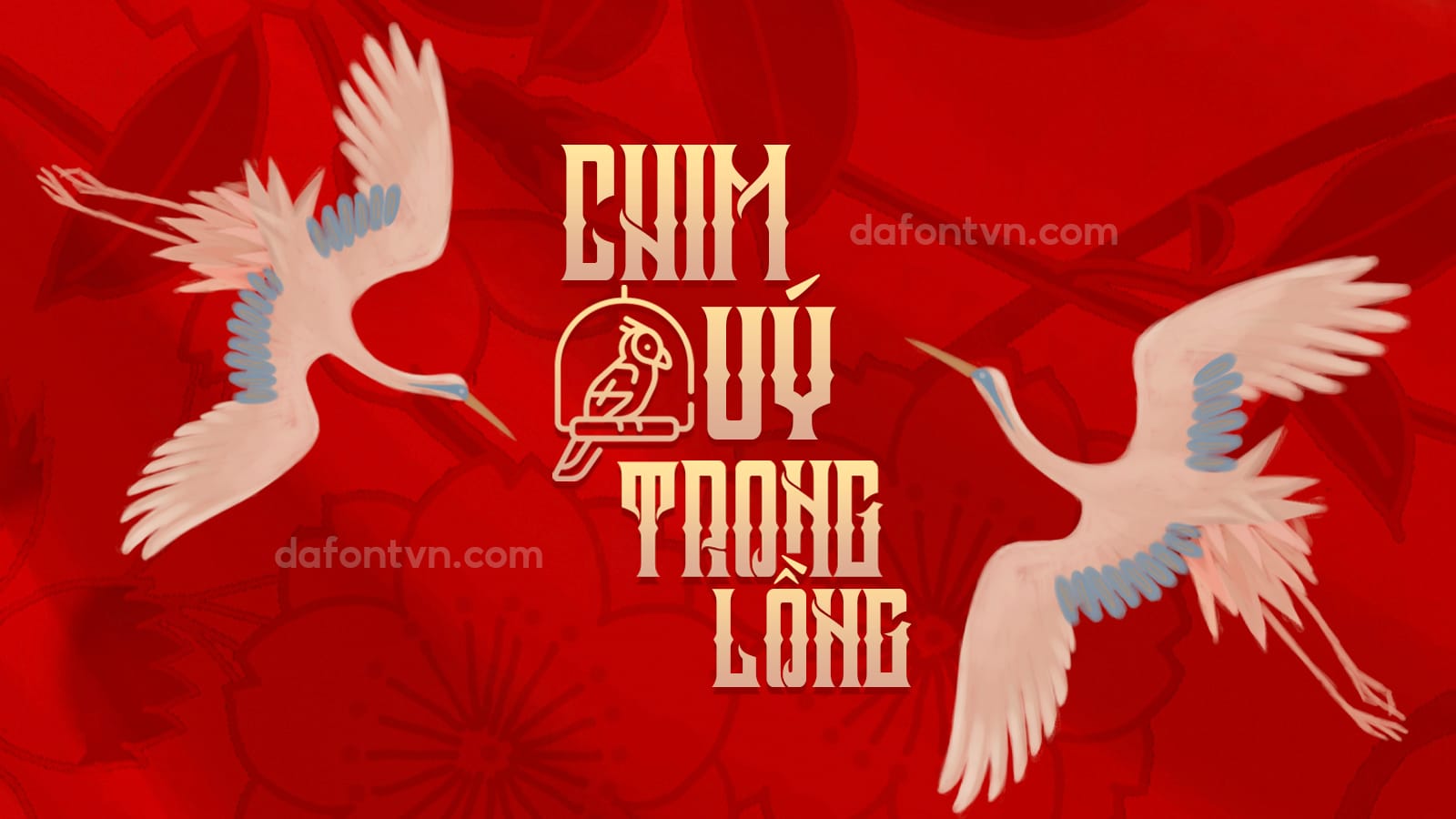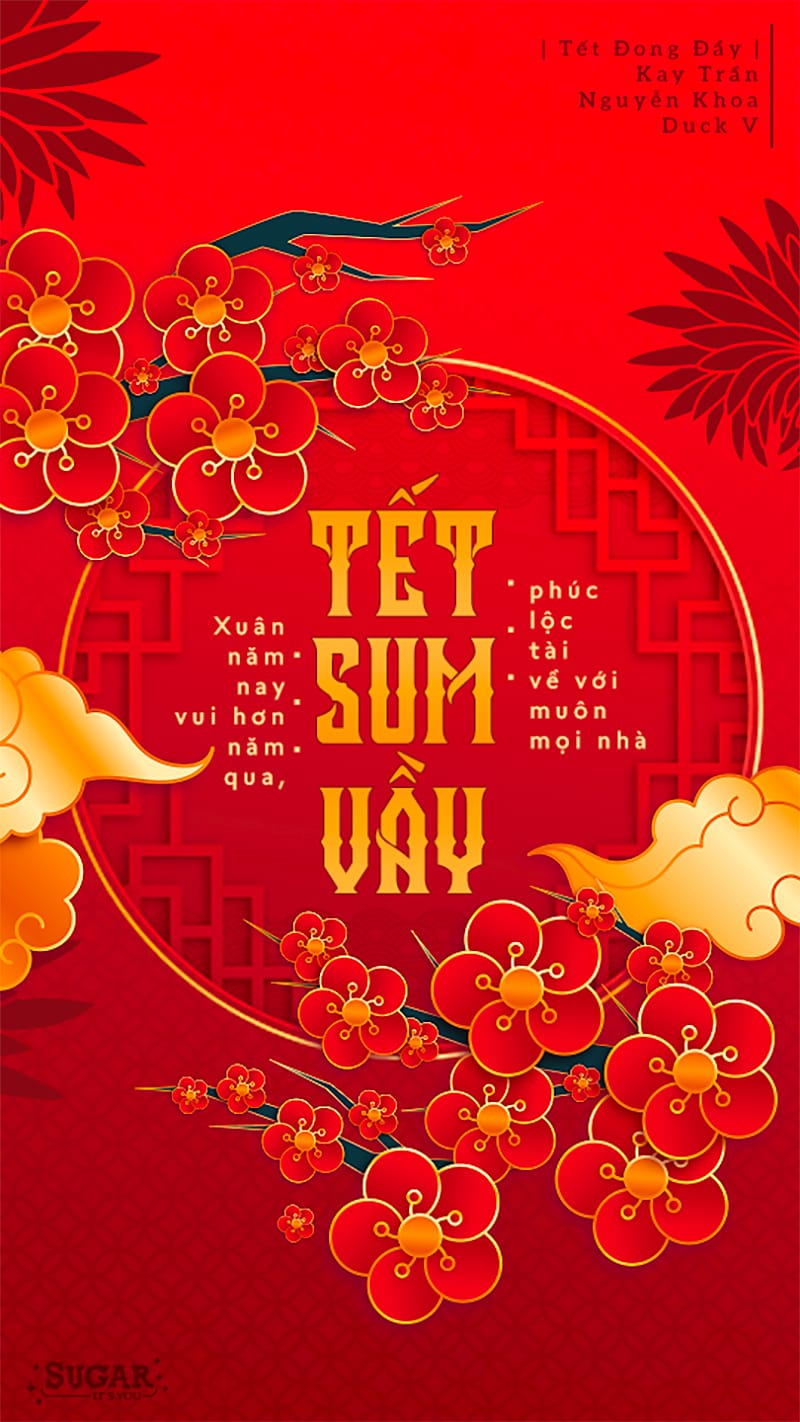
Font Crozzoe Việt Hóa – Font cực đẹp
Font Crozzoe Việt Hóa là một font chữ lấy cảm hứng từ phong cách Victoria. Kiểu chữ Crozzoe bao gồm đầy đủ các chữ cái viết hoa và viết thường cũng như hỗ trợ đa ngôn ngữ và đi kèm với một số glyph bổ sung.
Font Crozzoe tuy mang phong cách phương Tây nhưng rất thích hợp để các bạn design bìa truyện hoặc các ấn phẩm mang tính chất hoài cổ, cổ phong, thư pháp, v.v… Font việt hóa đầy đủ bởi Tuỳn, được kerning, feature lại cũng như tối ưu lại font.